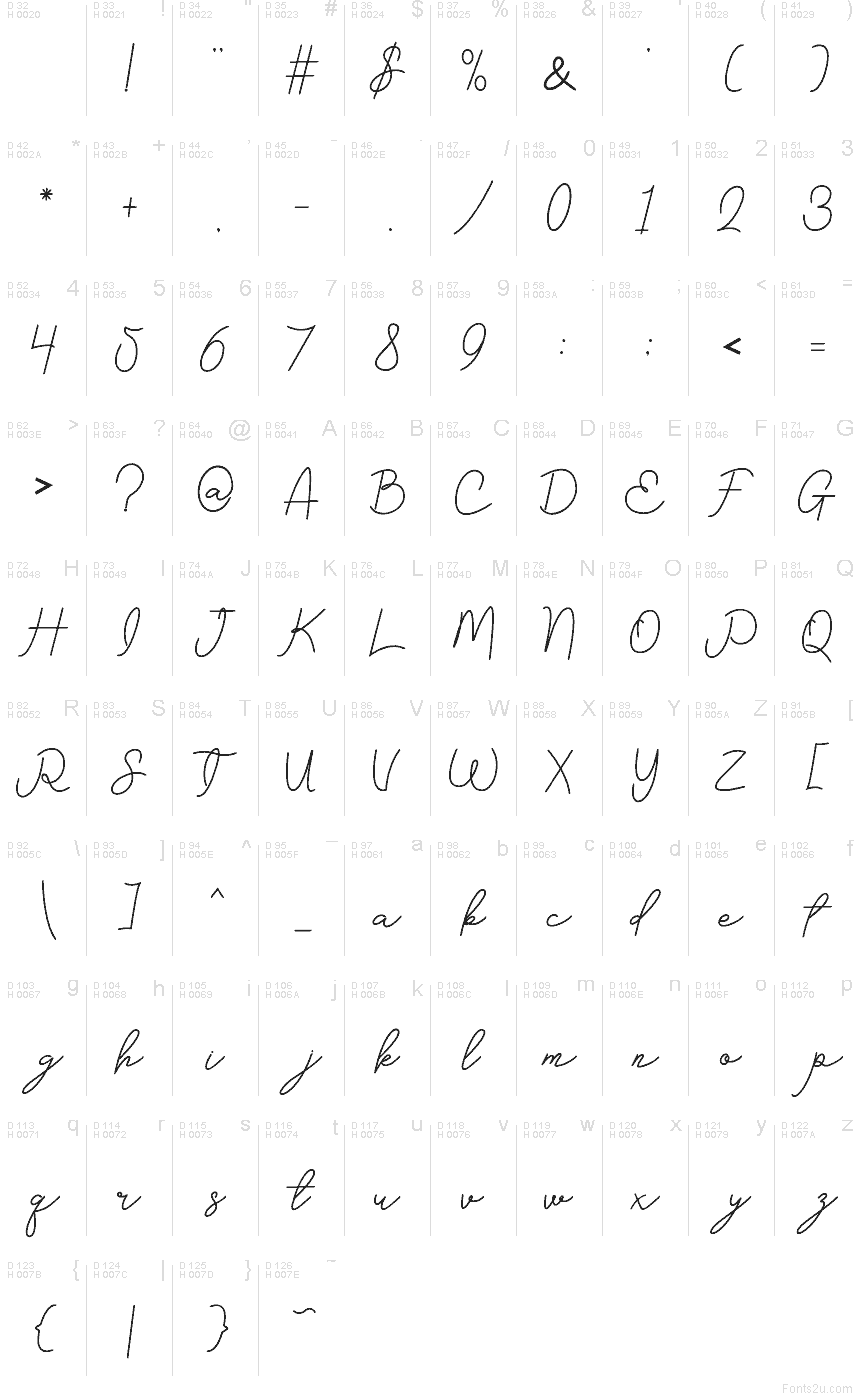
Pretty Satisfy Script
Pretty Satisfy Script od Putracetol Studio je bezplatné písmo v štýle rukopisu s ľahkým, plynulým rytmom a dlhými slučkami, vďaka ktorým sú písmená stále v pohybe. Línia ostáva hladká a rovnomerná, zatiaľ čo vysoké tvary a predĺžené ťahy dodávajú písmu uvoľnený, módny vzhľad, ktorý nepôsobí ako strohá kaligrafia.
Najlepšie vynikne na logách butikov, obaloch kozmetiky, svadobných tlačovinách, citátoch na sociálne siete alebo menu kaviarní, kde jeho vzdušný pohyb sám o sebe vytvára štýl. Krátke nadpisy a branding v štýle podpisu ťažia z jeho otvorených ťahov, najmä ak hľadáte niečo osobité, čo nepôsobí rustikálne alebo príliš ako hrubý štetec.